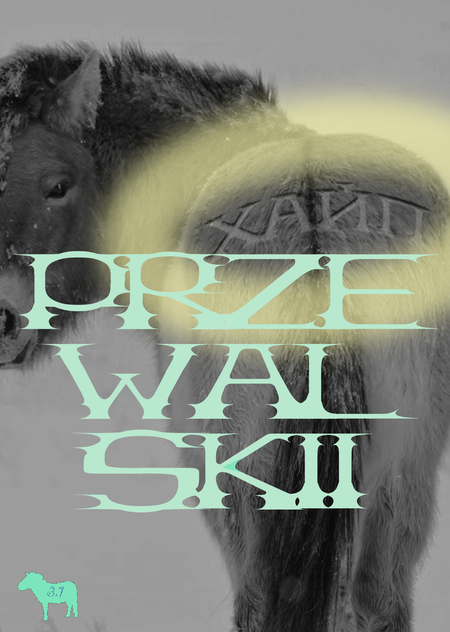
Шрифт «Пржевальский» посвящён диким лошадям, обитающим в степях. Визуально гарнитура повторяет особенности строения животных: пухлый корпус, острые гривы-ирокезы. Этих лошадей до сих пор никто не оседлал, чем обусловлен буйный вид моей работы.